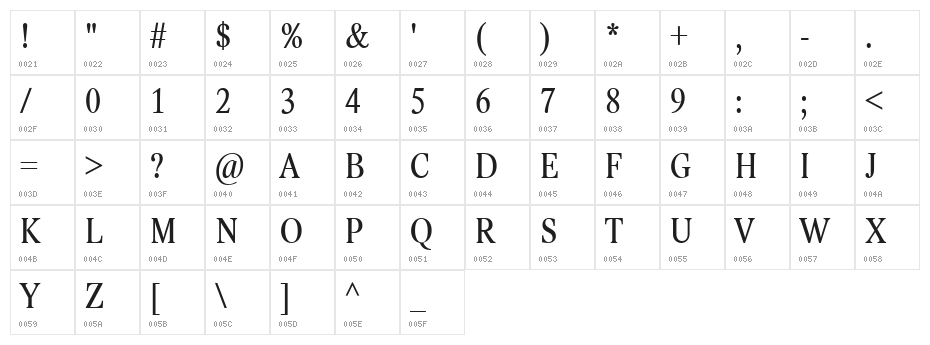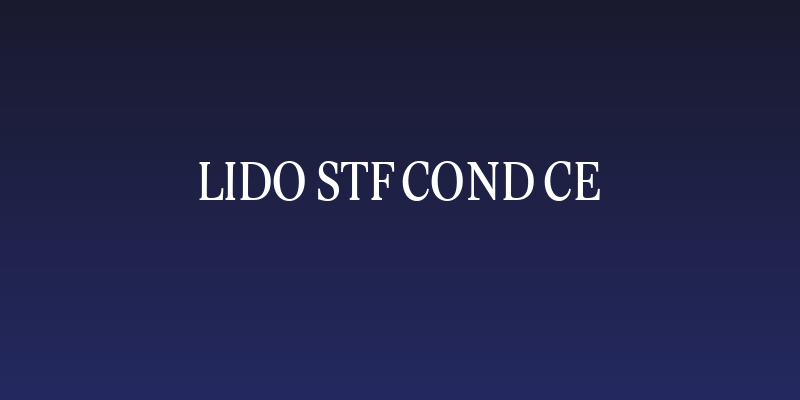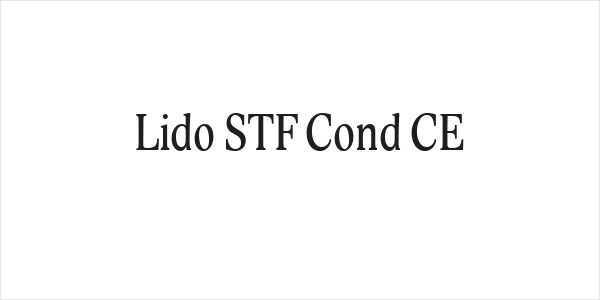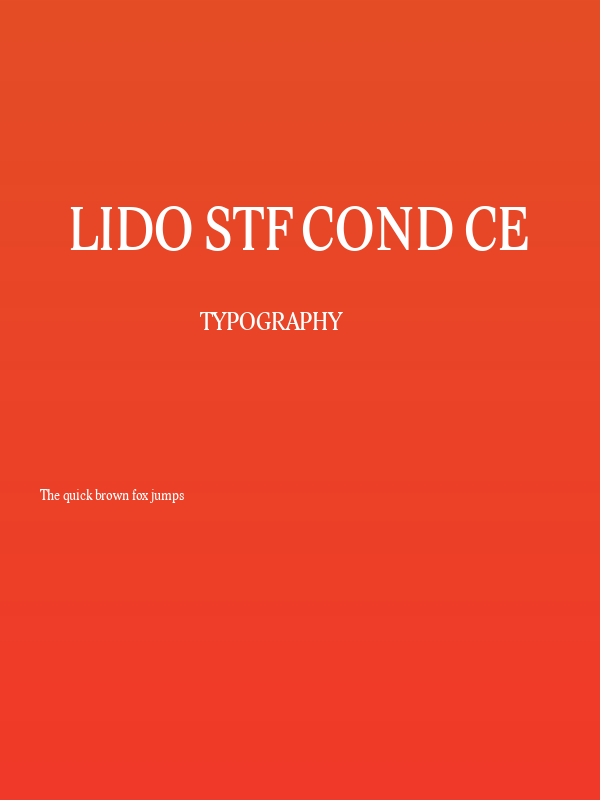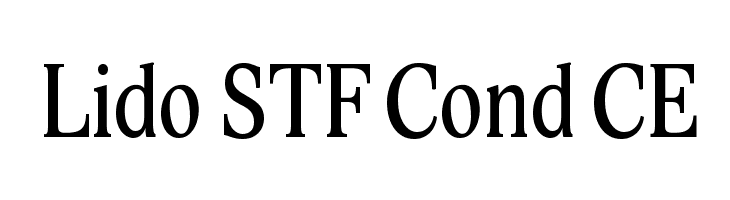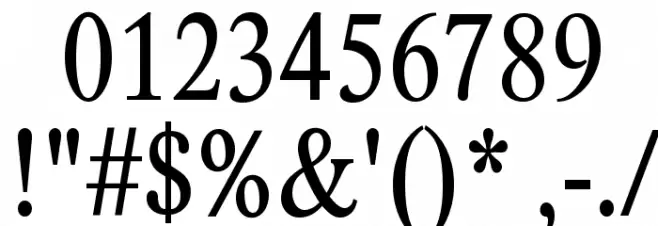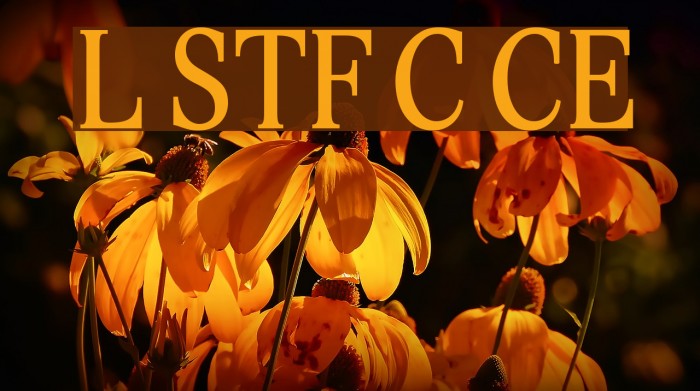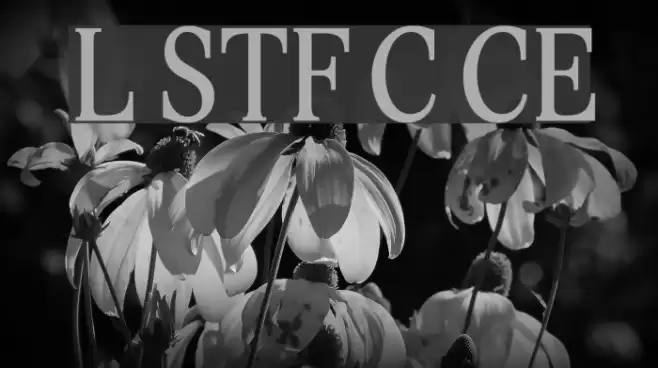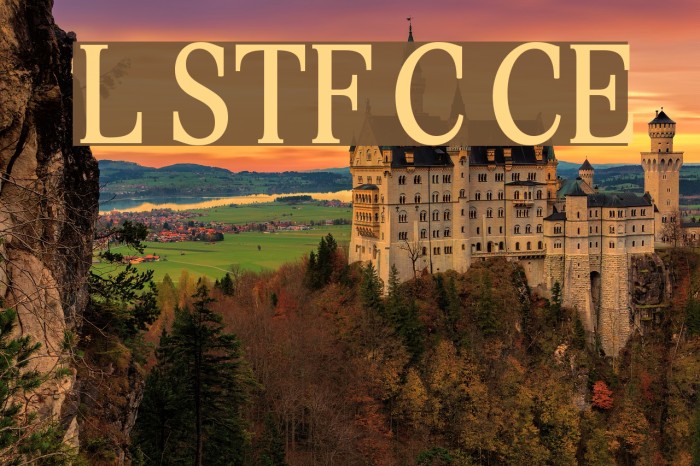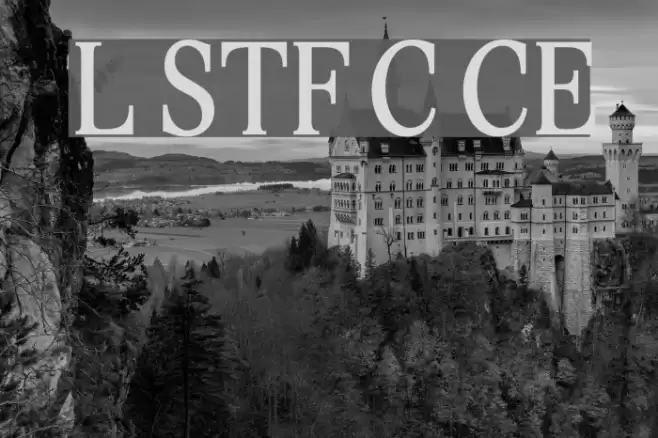
Lido STF Cond CE Font
| Gesamtstil | Classic |
| Anwendungsfall | Headlines, Body text, Editorial design |
| Vorgeschlagene Projekte | This font is perfect for editorial design, book publishing, corporate branding, and formal invitations. |